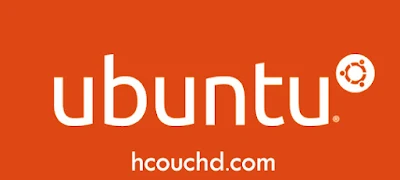
الخط الرائع Ubuntu من الخطوط المميزة لشركة دالتون ماغ، فكيف لا وهي الشركة المتخصصة بتصميم الخطوط منذ عام 1991 وقد تأسست من قبل برونو ماغ، ويعتبر هذا الخط من الخطوط المطورة والجميلة والتي تُستخدم بكثرة ومنتشرة بشكلٍ واسع خاصةً بأنها تدعم أكثر من لغة.